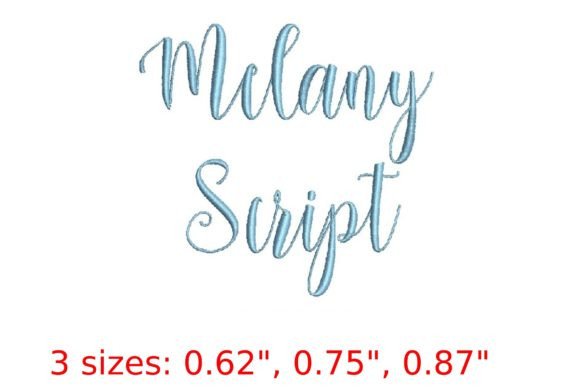
Melany Script Embroidery Font
Việc tìm kiếm các thành phần thiết kế phù hợp có thể là một thách thức, nhưng Melany Script Embroidery Font cung cấp một bộ sưu tập đặc biệt giúp nâng tầm công việc của bạn ngay lập tức.
Được chế tác với độ chính xác cao, Melany Script Embroidery Font cung cấp các vector sạch, kiểu chữ mượt mà và giấy phép thương mại để bạn yên tâm.
Hoàn hảo cho thợ thủ công, nhà thiết kế đồ họa và chủ doanh nghiệp nhỏ muốn thêm nét chuyên nghiệp vào hàng hóa của họ.